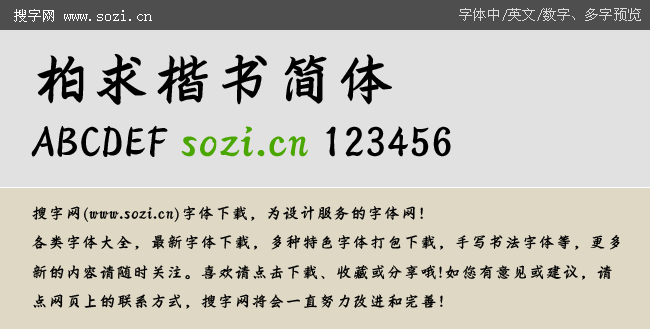
方正字跡-柏求楷書(shū)簡(jiǎn)體
搜字網(wǎng)給大家提供一款方正字跡-柏求楷書(shū)簡(jiǎn)體中文字體下載。方正字跡-柏求楷書(shū)簡(jiǎn)體是一款非常漂亮的楷體字體,字形流暢大方,效果十分漂亮。此款字體適用于包裝設(shè)計(jì)、廣告設(shè)計(jì)、海報(bào)設(shè)計(jì)等視覺(jué)環(huán)境。